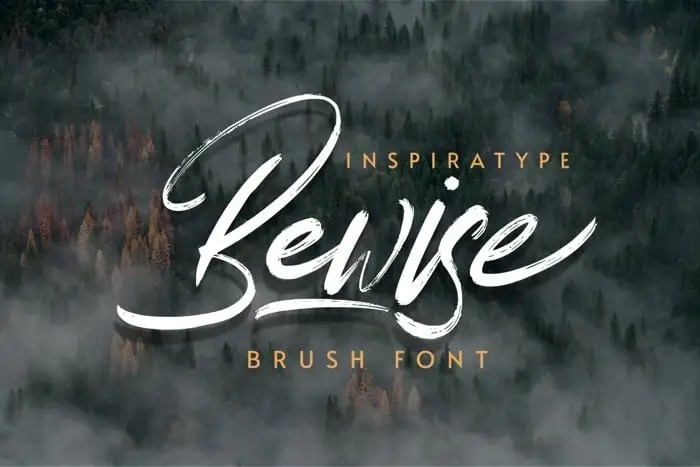
Bewise Brush Font – Download Grátis
A Bewise Brush Font é uma tipografia script robusta criada a partir de traçados manuais com elementos urbanos frescos que combinam linhas arredondadas elegantes. Esta fonte vem completa com letras maiúsculas e minúsculas, numerais, pontuação e várias variações em cada caractere, incluindo alternativas de tipo OpenType, ligaturas comuns e até mesmo swashes adicionais que permitem um toque personalizado para seus designs. Perfeito para criação de logotipos, cartões de papelão, outdoors, roupas designadas, etiquetas e muito mais. Seja você uma agência de design ou apenas alguém que busca novas maneiras de expressar sua identidade visual, a Bewise Brush Font é um ótimo complemento para seu arsenal de ferramentas de design.